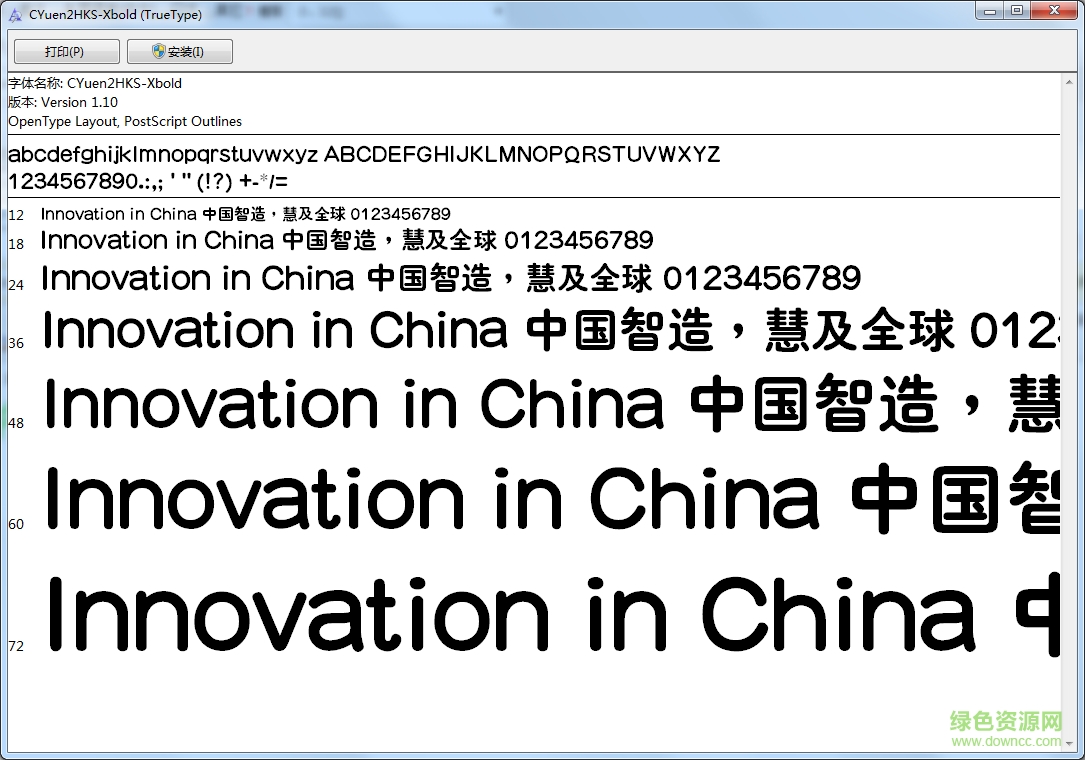
蒙納簡(jiǎn)粗圓二字體是一款非常漂亮的蒙納字體,既然是粗體,當(dāng)然自帶了加粗效果,非常的醒目,在廣告和包裝設(shè)計(jì)中使用非常的方便,歡迎有需要的朋友到綠色資源網(wǎng)下載體驗(yàn)吧
該字體以商用為主,字形端正大方,整體效果非常不錯(cuò),但唯一的缺點(diǎn)就是可以有點(diǎn)簡(jiǎn)體字不能正常顯示。可以應(yīng)用于廣告設(shè)計(jì)、平面設(shè)計(jì)、印刷包裝、報(bào)紙雜志等行業(yè),使用時(shí)請(qǐng)選擇“MGentle hks xbold”即可,喜歡的用戶可免費(fèi)下載收藏。